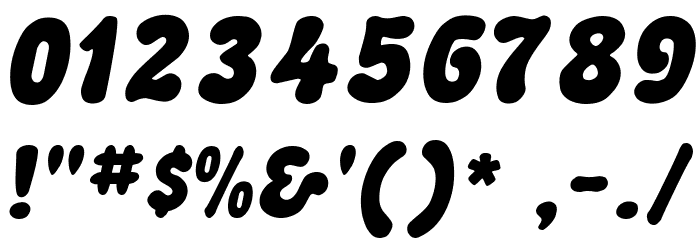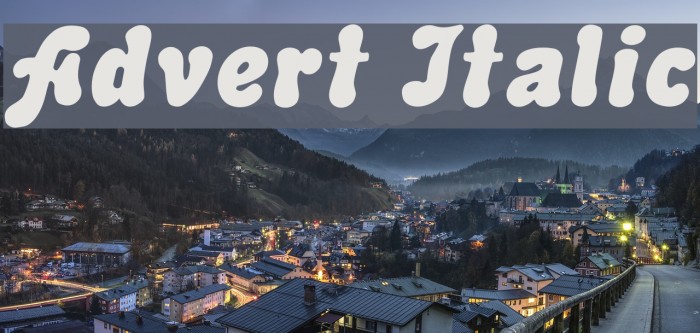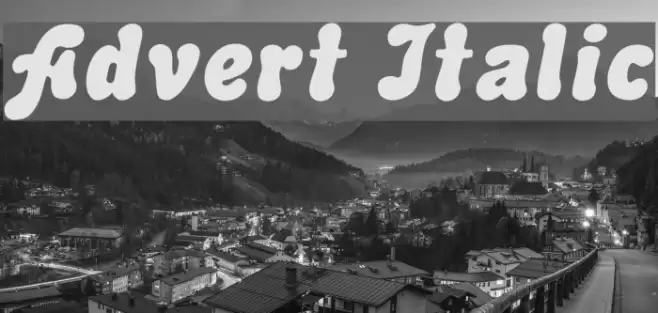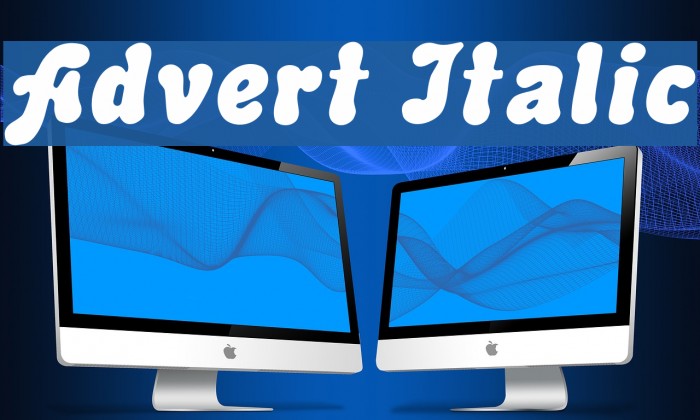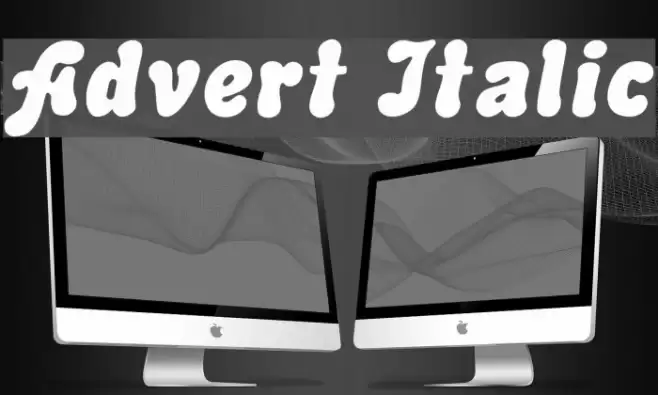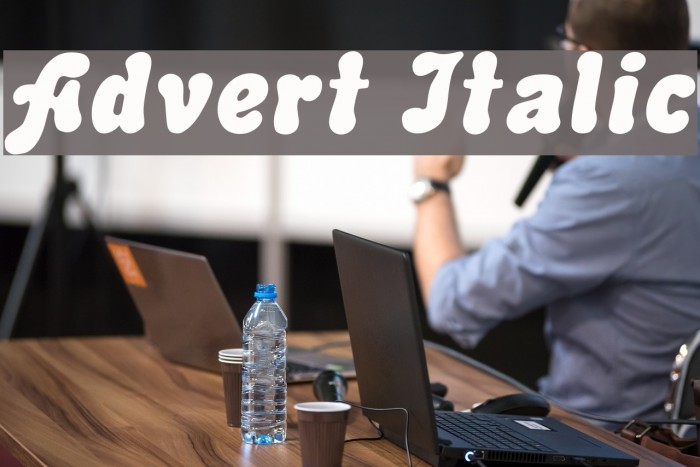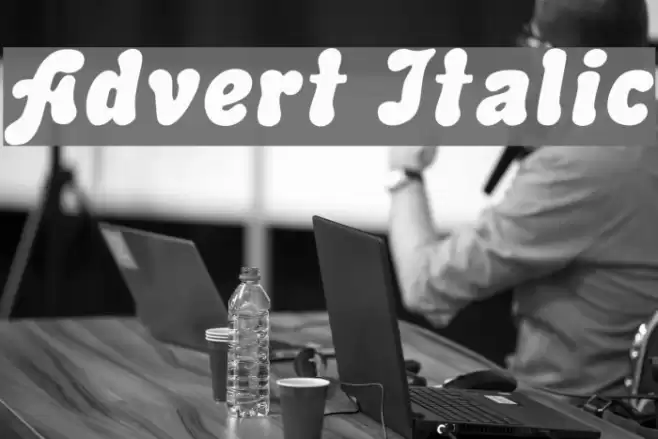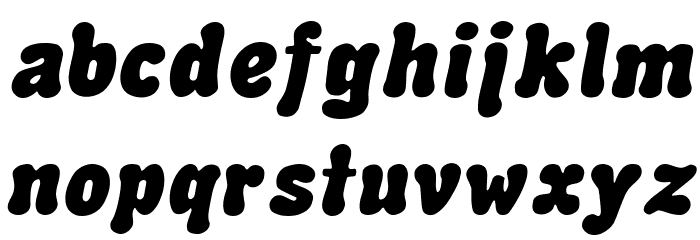
Advert Italic Font
| Estilo general | Vintage, Playful |
| Proyectos propuestos | Ideal for retro-themed posters, playful branding, eye-catching headlines, and creative advertising campaigns. |